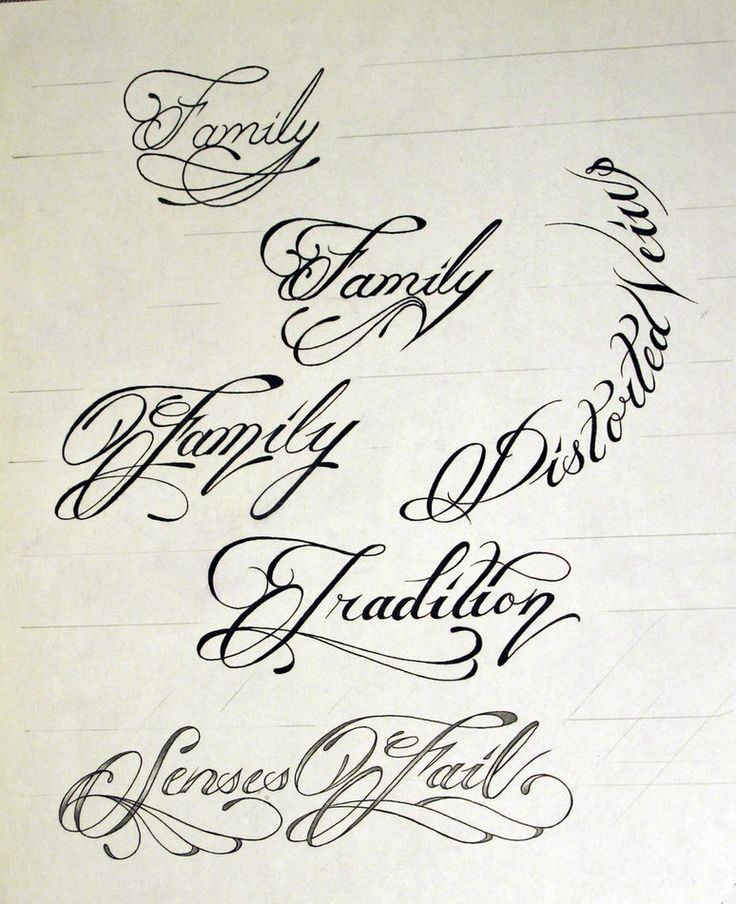
Слово привет красивым шрифтом
Посмотрите больше идей на темы Каллиграфия, Рукописные шрифты и. Карточки для скрапбукинга с русским календарём, красивые надписи от руки.
Some design examples showing the new Hello Beautiful brush script font.
Красивая надпись family. Красивые татуировки надписи для девушек и мужчин, фото.
Татуировки с надписями в последнее время набирают популярность и в Европе и в других странах. Такие тату сделали себе многие звезды голливуда. Надписи смотрятся великолепно и оригинально. При помощи надписи иногда гораздо легче передать смысл, чем с помощью рисунка. Что бы такая татуировка не выглядела нелепо, главное правильно подобрать шрифты для татуировок.
В основном шрифт зависит от языка. Обычно для татуировок с надписями выбирают английский язык, как общемировой. Кроме того в английском языке латинские буквы, а они выглядят намного привлекательнее наших «Щ» и «Ы».
В качестве шрифта для тату с надписью чаще всего используют каллиграфические шрифты, любые шрифы с вензелями. В английском языке красивых каллиграфических шрифтов намного больше, чем в русском. Для выбора шрифта для татуировки нужно определиться будет ли это фраза или одно слово. Если татуировка представляет из себя слово, начинающееся с заглавной буквы, нужно помнить, что не все заглавные буквы выглядят хорошо.
Нужно учесть что бы шрифт был читаемым. Лучше не использовать черезчур мелкие шрифты и тонкие линии близко расположеные друг к другу. Со временем татуировки немного размываются и мелкая строчка может превратится в нечитаемое пятно.
- Шрифты для пишущей машинки однозначно напоминают образ пишущей машинки. Стилизованные под старину и словно пахнущие типографикой, они понравятся любителям ретро и винтажа.
- Curly Fonts — красивые шрифты для тату и безобидный вариант для тех, кто хочет намекнуть на свою игривость и задор.
Я просто открыл «Фотошоп» и подобрал нужный шрифт. Дизайнер одобрил результат моей работы.